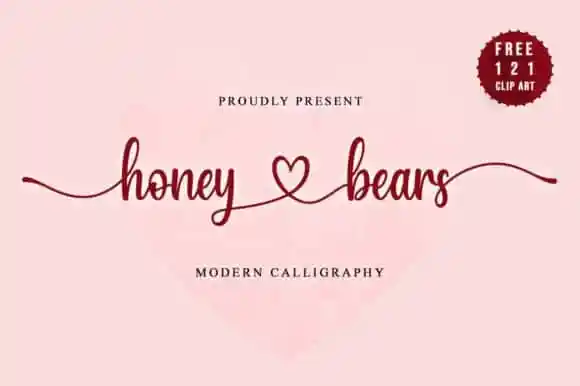
A Honey Bears Calligraphy Font é uma elegante seleção do catálogo de fóruns script modernas que se conecta ao coração com seu belo estilo, criado para apresentar um design luxuoso de alta qualidade. Inspirada pela natureza onírica dos leões e por seus doces ninhos, a fonte é perfeitamente adaptada para invitações, cartões de agradecimento, citações, cartas de boas-vindas, logotipos e cartões de visita. Ela se destaca em qualquer design que possa ter um toque romântico. Adicionalmente, o fato de ser PUA encoded significa que você pode acessar todos os símbolos e swashes facilmente. Esta característica torna a Honey Bears Calligraphy Font uma opção indispensável para quem está buscando uma fonte que possa adicionar um toque único e sofisticado aos seus projetos gráficos. Através do formato de fóruns script, essa font oferece a você um meio perfeito para incluir elementos charmosos e sutis em seu design.